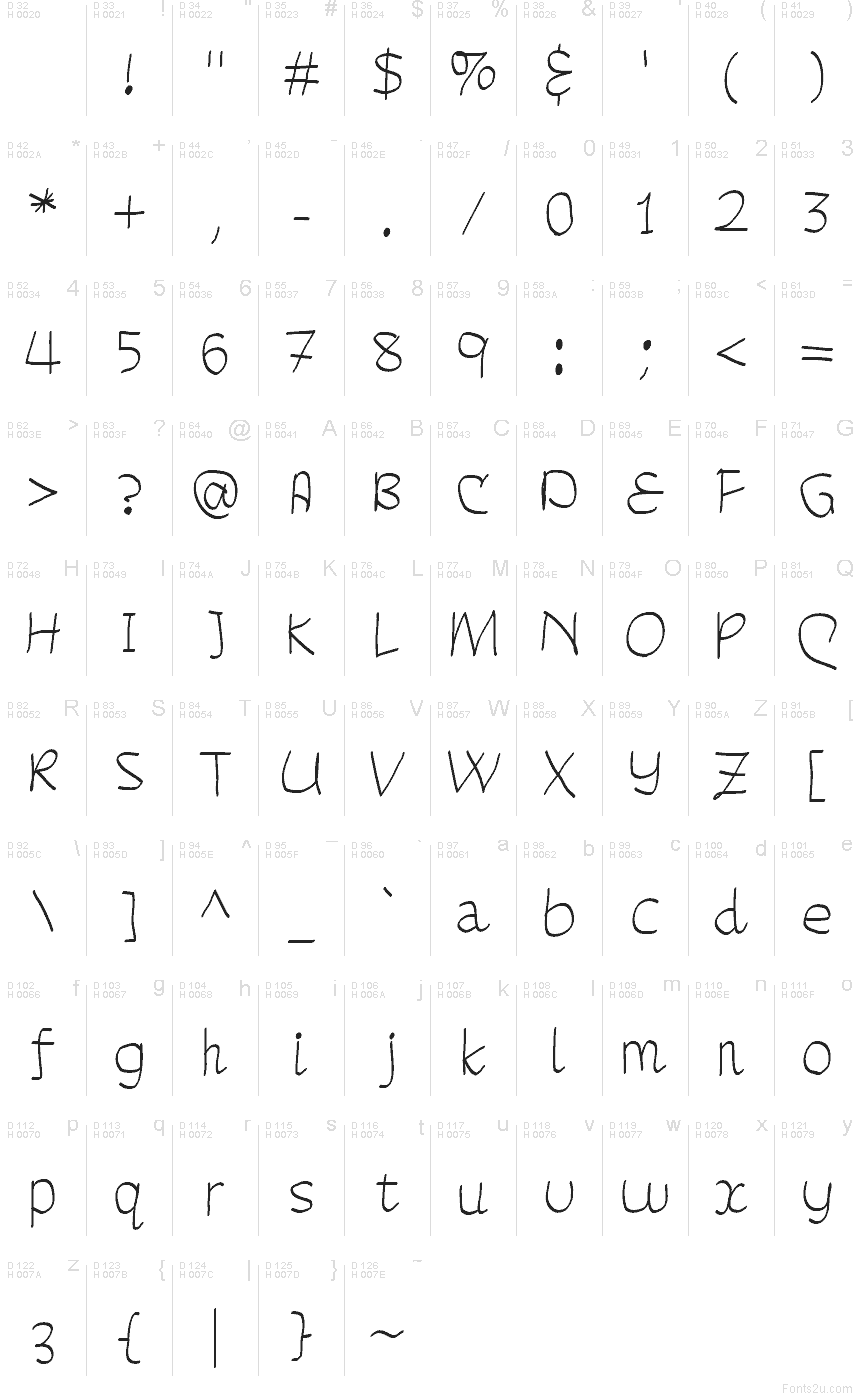
AOW11Hand Fully Regular
AOW11Hand Fully é uma fonte manuscrita gratuita definida por traços longos e fluidos, com um ritmo solto e vertical que parece ter sido desenhado num único movimento rápido. As letras mantêm-se simples e abertas, com formas arredondadas misturadas com curvas mais acentuadas, conferindo-lhe a irregularidade casual de uma escrita à mão real, em vez de uma caligrafia polida.
Esta textura direta e pessoal faz todo o sentido em citações estilo notas, logótipos casuais, rótulos de produtos, cartões de felicitações e gráficos para redes sociais, onde um texto comum pareceria demasiado formal. Títulos curtos e embalagens beneficiam especialmente do seu ritmo alto e levemente irregular, que mantém a mensagem humana e autêntica.